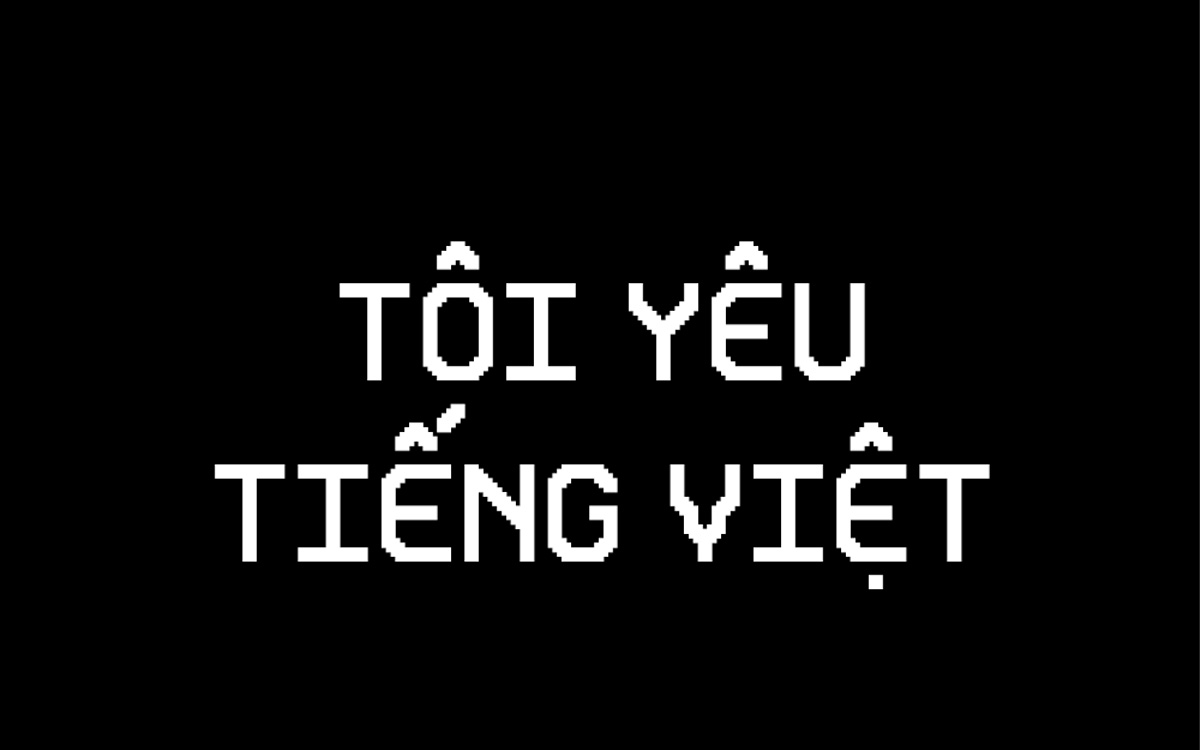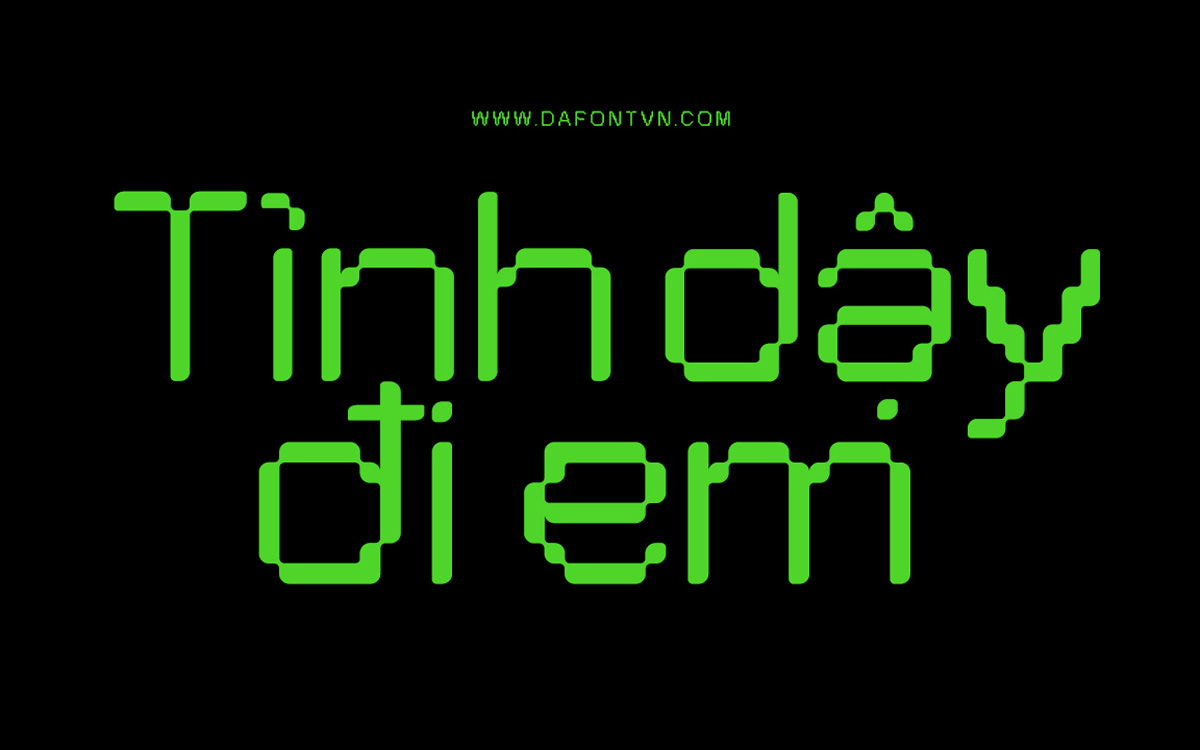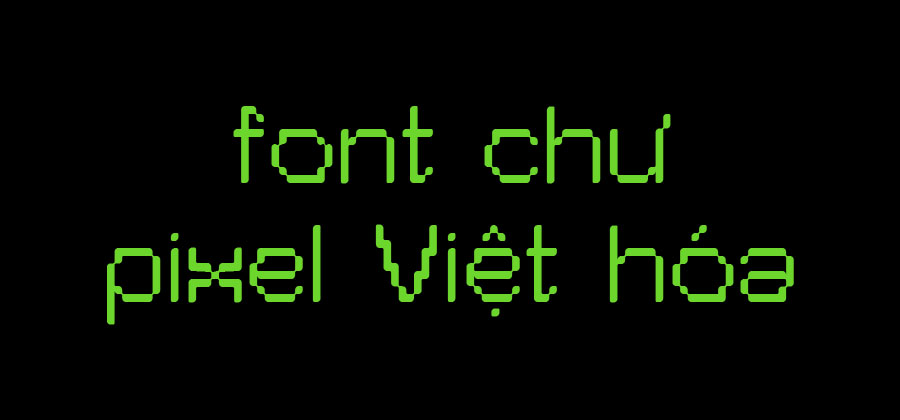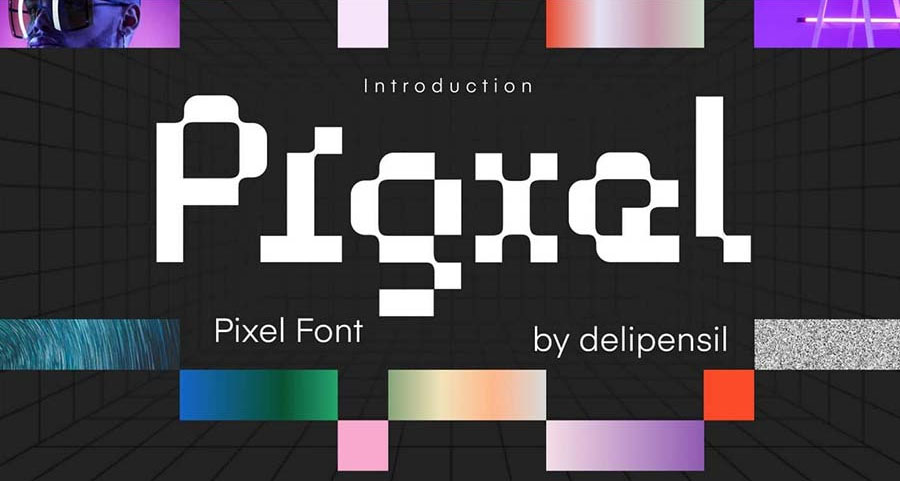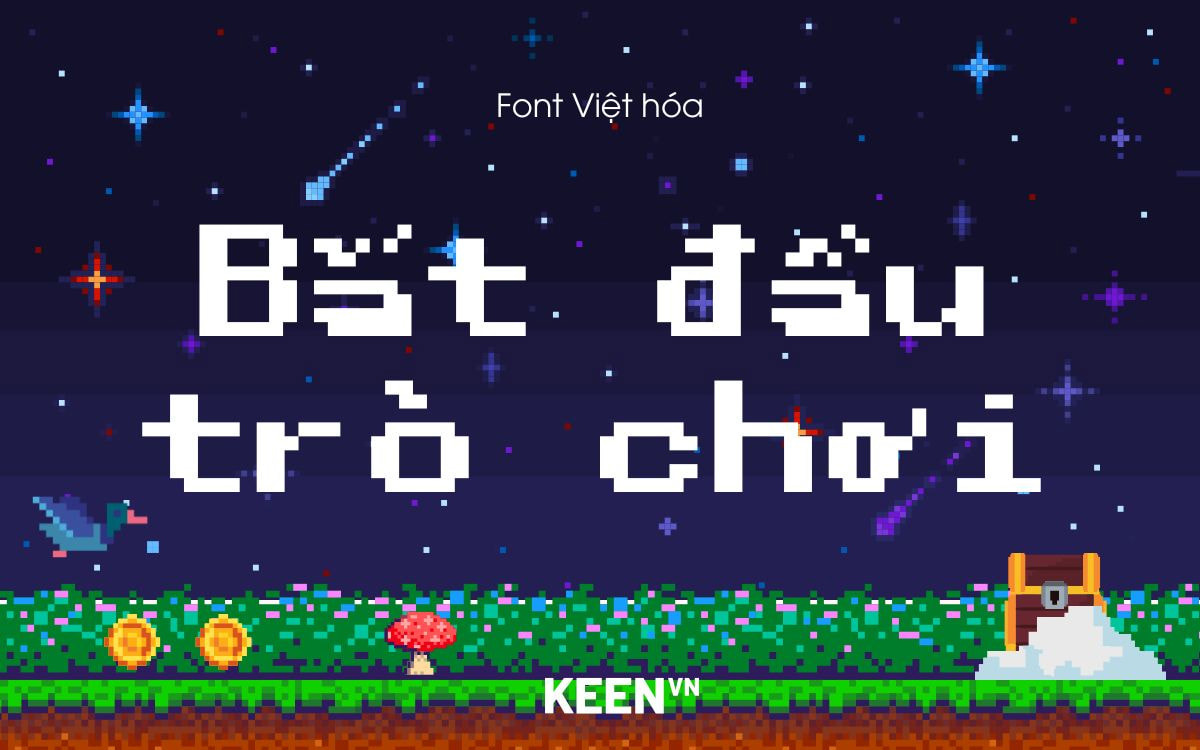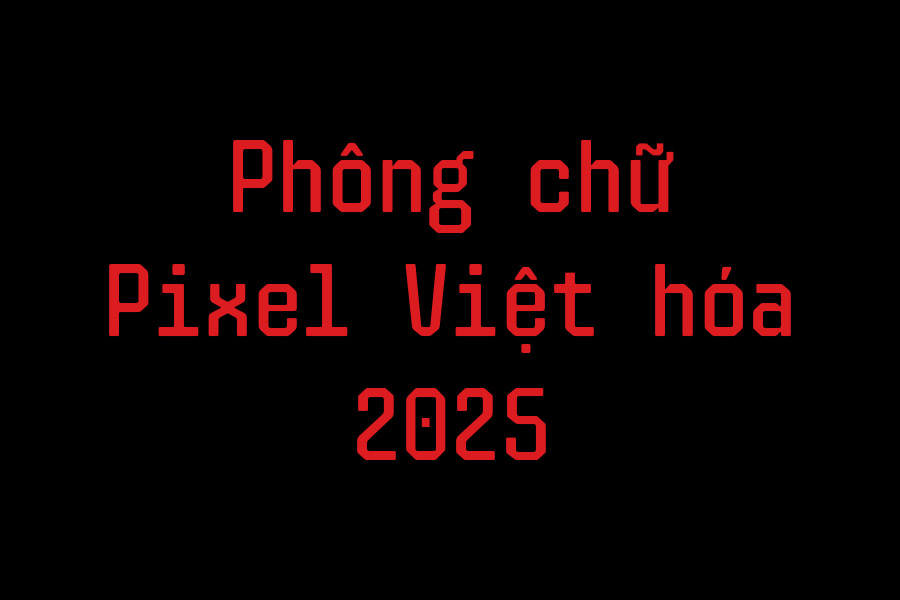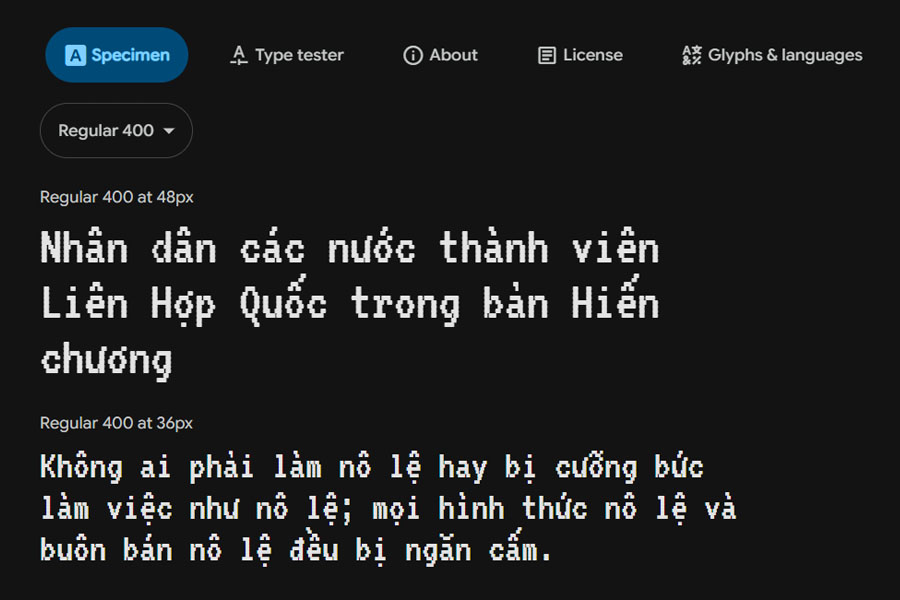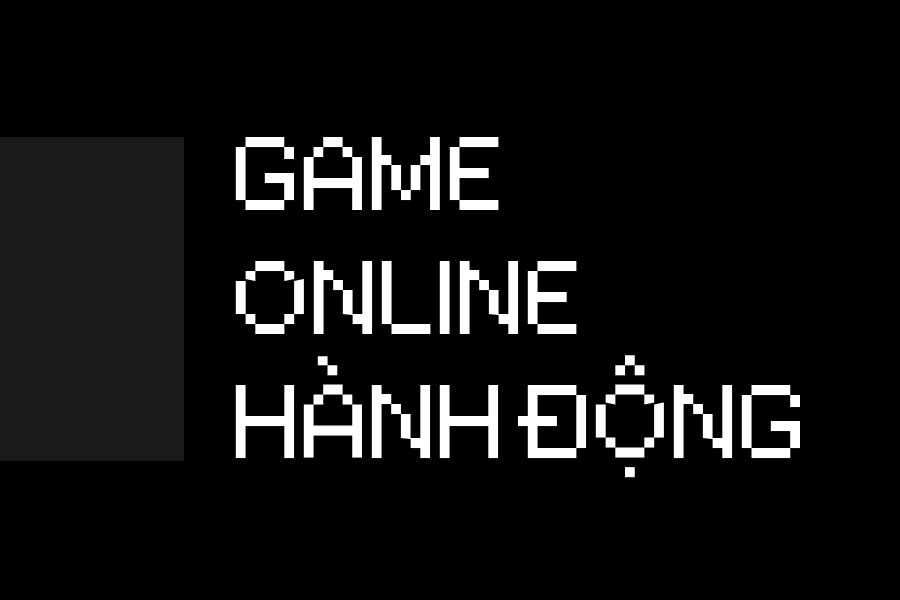
Bạn đang tìm một kiểu chữ đậm chất game cổ điển hoặc mang hơi hướng pixel art? Nếu vậy, font chữ pixel chính là lựa chọn không thể bỏ qua. Những bộ font này không chỉ tái hiện cảm giác thiết kế 8-bit quen thuộc mà còn giúp bạn tạo nên những layout độc đáo, cá tính và mang đậm dấu ấn riêng. Trong bài viết này, mình sẽ gợi ý cho bạn hơn 10 font chữ pixel Việt hóa đẹp nhất năm 2025 – dễ tải, dễ dùng, ứng dụng được trong nhiều phong cách thiết kế khác nhau. Cùng khám phá nhé!
Font chữ pixel là gì?
Font chữ pixel là kiểu chữ được tạo nên từ những ô vuông nhỏ liền kề – giống như các điểm ảnh (pixel) trên màn hình. Mỗi ký tự trong font đều mang hình khối rõ ràng, vuông vức, tái hiện đúng cảm giác “low-resolution” của thời kỳ đầu công nghệ số.
Những font này từng xuất hiện phổ biến trong các trò chơi điện tử kinh điển như Mario, Contra, hoặc trên các hệ điều hành máy tính cũ. Dù mang đậm phong cách cổ điển, font pixel hiện nay đã được “tái sinh” với nhiều biến thể mới mẻ, đầy tính sáng tạo.
Đặc điểm nhận diện của font chữ pixel
Một vài đặc điểm đặc trưng giúp bạn dễ dàng nhận biết font pixel:
- Nét chữ vuông vức, rõ ràng, không bo tròn.
- Mang đậm phong cách 8-bit hoặc 16-bit cổ điển
- Thường phát huy hiệu quả tốt nhất khi dùng ở kích cỡ nhỏ (dưới 16px).
- Nhiều font đã được Việt hóa đầy đủ, sẵn sàng dùng trong thiết kế tiếng Việt.
Danh Sách 10 Font Pixel Việt Hóa Đẹp Nhất 2025
Dưới đây là bộ sưu tập những font chữ pixel được chọn lọc kỹ càng, đã được Việt hóa và dễ dàng sử dụng cho cả thiết kế in ấn và digital:
1. Font chữ pixel Neue Pixel Grotesk Việt hóa Hiện đại
Neue Pixel Grotesk mang phong cách pixel hiện đại kết hợp cấu trúc sans-serif tối giản. Font sử dụng lưới điểm ảnh vuông giúp từng ký tự hiển thị sắc nét, rõ ràng và nhất quán trong toàn bộ hệ thống chữ. Các cạnh được xử lý sắc sảo và có tính đồng bộ cao, mang tính chất hình học cao. Phông chữ này thể hiện sự logic và có tổ chức, rất phù hợp cho các dự án cần sự rõ ràng về cấu trúc hoặc kiểu chữ độc đáo trong nhóm pixel.
- Tác giả gốc: M35 (studio thiết kế tại Úc, phát hành năm 2018)
2. Font chữ VT323 Việt hóa Phong cách pixel cổ điển, retro
VT323 là một font chữ pixel dạng display với kiểu dáng mạnh mẽ, dễ nhận diện. Mọi con chữ đều sử dụng dạng khối vuông lớn, tạo hiệu ứng sắc cạnh rõ rệt. Đường nét thẳng đứng, dày và có sự đồng nhất cao giữa các chữ cái, mang lại cảm giác hoài cổ nhưng không kém phần nổi bật. Phông chữ này rất phù hợp cho tiêu đề, biển hiệu hoặc thiết kế cần nhấn mạnh yếu tố retro và cá tính riêng biệt.
- Tác giả gốc: Peter Hull
3. Font chữ Pixel công nghệ TH Degrad Mono Việt hóa
TH Degrad Mono mang kiểu dáng monospaced kết hợp với phong cách pixel cách điệu. Mọi ký tự giữ tỷ lệ chiều rộng đồng nhất, tạo cảm giác gọn gàng và cân đối. Hình dạng sắc cạnh, cắt nét gọn gàng và hiện đại, phần chân – đầu chữ được xử lý tinh tế tạo điểm nhấn hiện đại. Kiểu chữ này vừa giữ được tinh thần cổ điển của pixel font, vừa thể hiện sự sắc sảo trong thiết kế kỹ thuật số.
- Tác giả gốc: Holyline Design
- Việt hóa bởi: Phạm Sơn - Admin S99, Fontdep.vn
4. Phông chữ FVF Fernando 08 Việt hóa – Gọn Gàng & Vui Mắt
FVF Fernando 08 là một font chữ pixel có thiết kế tinh tế và đều đặn. Các nét chữ được xây dựng từ khối vuông nhỏ, độ dày vừa phải, tạo nên cảm giác nhẹ nhàng, dễ đọc. Kiểu dáng cân đối và có chút phá cách ở một số ký tự giúp tổng thể trở nên sinh động hơn. Đây là lựa chọn lý tưởng cho các thiết kế mang tính trẻ trung, thân thiện hoặc chủ đề gần gũi với công nghệ, giáo dục.
- Tác giả gốc: FVF
- Việt hóa bởi: FVF
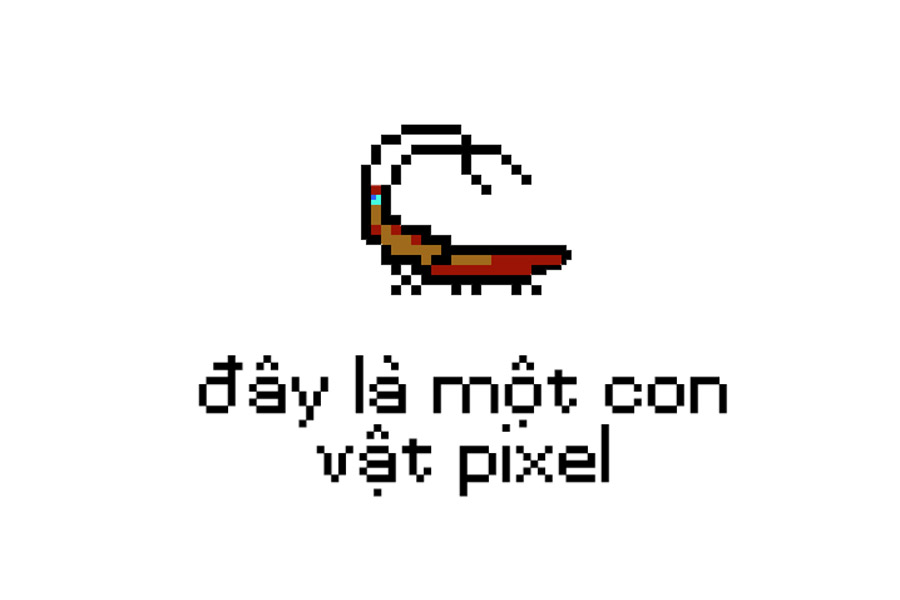
5. Font chữ SVN-Coder's Crux Việt hóa Tối Giản
SVN-Coder's Crux mang phong cách pixel truyền thống với kiểu dáng vuông vức, thẳng hàng và rõ nét. Các ký tự được tạo nên từ lưới điểm ảnh cơ bản, giữ đúng tinh thần thiết kế của font monospace. Nhờ độ cân đối và tỷ lệ đồng nhất, phông chữ này đặc biệt rất thích hợp khi sử dụng trong các giao diện lập trình hoặc game đơn giản hoặc thiết kế cần truyền tải thông tin ngắn gọn, dễ nhìn.
- Việt hóa bởi: SVN Team
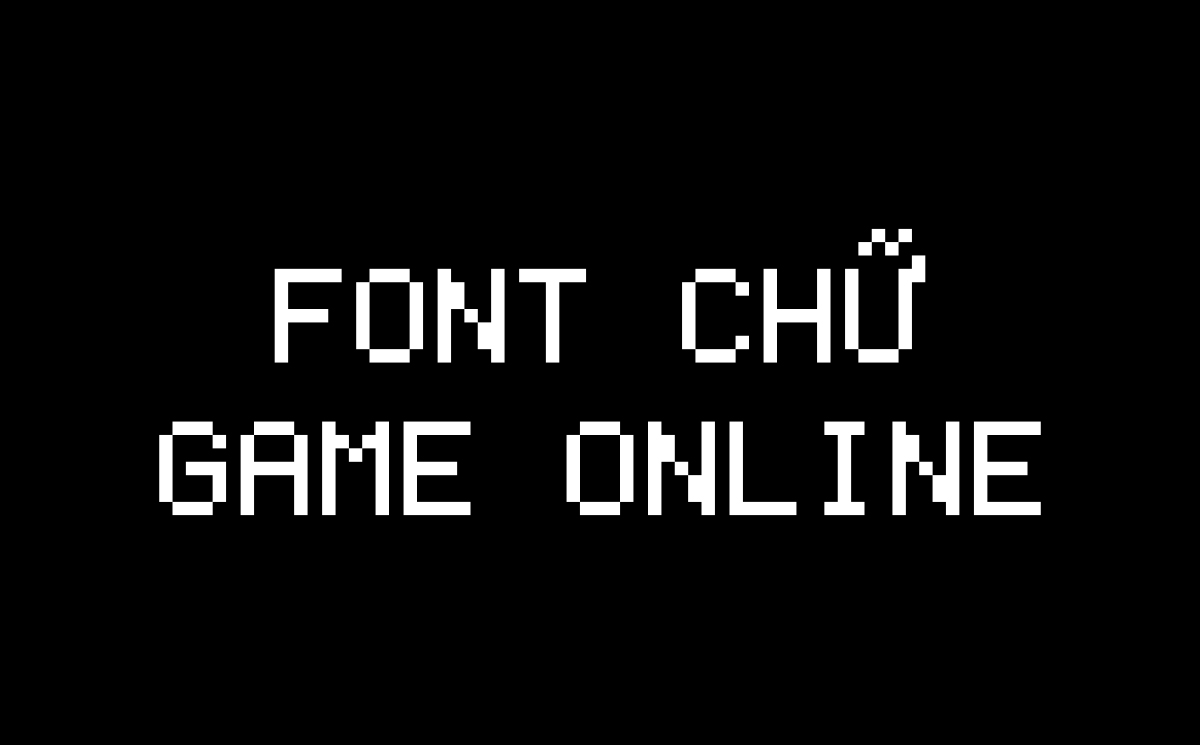
6. Font chữ SVNm Retron 2000 – Pixel Retro Việt Hóa Cho Game
SVN-Retron 2000 tái hiện tinh thần pixel cổ điển từ những năm đầu của kỷ nguyên game console. Toàn bộ chữ cái mô phỏng từ lưới pixel vuông, cân đối, với nét dày và đều nhau, tạo nên tổng thể mạnh mẽ và dễ đọc. Font giữ nguyên phong cách monospaced cổ điển, đặc biệt nổi bật khi sử dụng ở cỡ lớn. Đây là lựa chọn tuyệt vời cho thiết kế tiêu đề mang phong cách hoài cổ, công nghệ và retro.
- Việt hóa bởi: SVN Team
→ Silkscreen có độ rõ nét cao, rất dễ đọc trong giao diện UI. Nếu bạn cần kết hợp giữa độ thẩm mỹ và khả năng đọc tốt, VT323 cũng là lựa chọn đáng cân nhắc.
Font pixel không chỉ là một xu hướng hoài cổ – mà còn là một phong cách thiết kế cá tính, sáng tạo và đậm dấu ấn cá nhân. Từ game retro đến đồ họa công nghệ, những kiểu chữ này luôn mang lại cảm hứng mới lạ cho bất kỳ ai yêu thích sáng tạo.